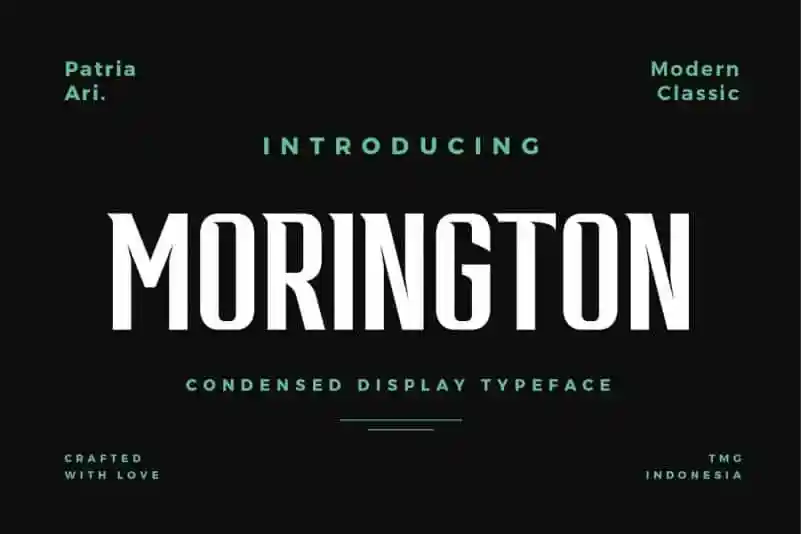
Morington Display Font – Fonte Grátis
Morington Display Font
A Morington Display Font é uma combinação única de estilos moderno e clássico, oferecendo uma opção perfeita para designers que buscam manter os olhos voltados tanto para temas futuristas quanto tradicionais. Desenvolvida pelo Patria Ari Typestudio, esta fonte condensada e forte proporciona um gráfico poderoso ideal para estilos modernos ou clássicos mais elaborados. Seja você um designer de arte digital ou uma empresa criando materiais imprensáveis, a Morington Display Font é uma excelente escolha que manterá sua identidade visual atual e elegante. Para quem está procurando por uma fonte para o tipo impresso moderna, mas com um toque clássico, essa opção pode ser perfeita. Seja em letras grandes ou pequenas, a Morington Display Font permite expressar seu design de maneira única e poderosa, mantendo uma conexão estética com padrões mais tradicionais. Não importa se você está trabalhando num projeto que exige um estilo contemporâneo ou se está criando materiais para clientes que apreciam algo antigo e sofisticado, a Morington Display Font pode ser o elemento gráfico perfeito para seu trabalho.